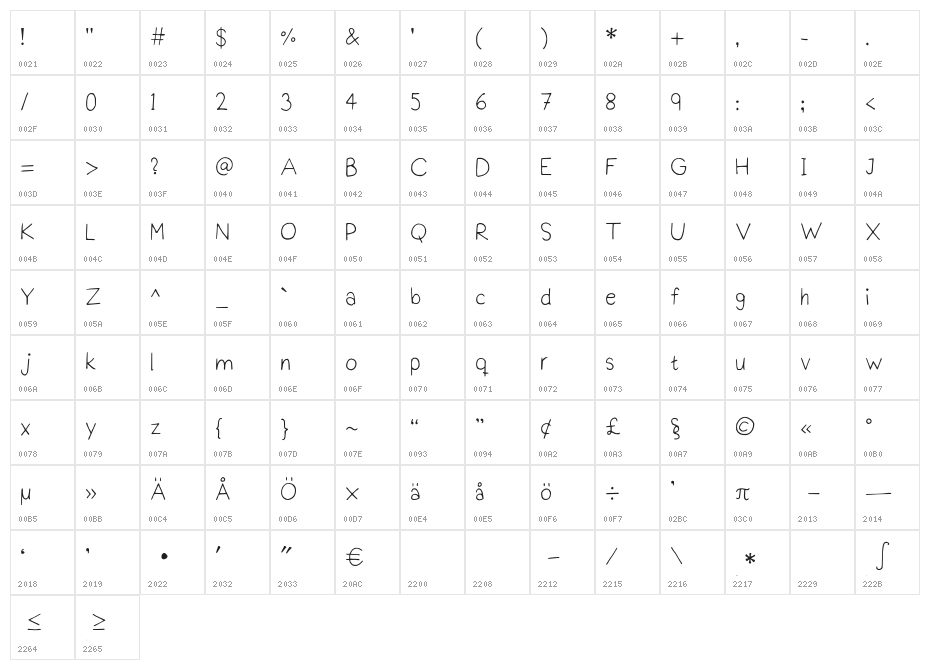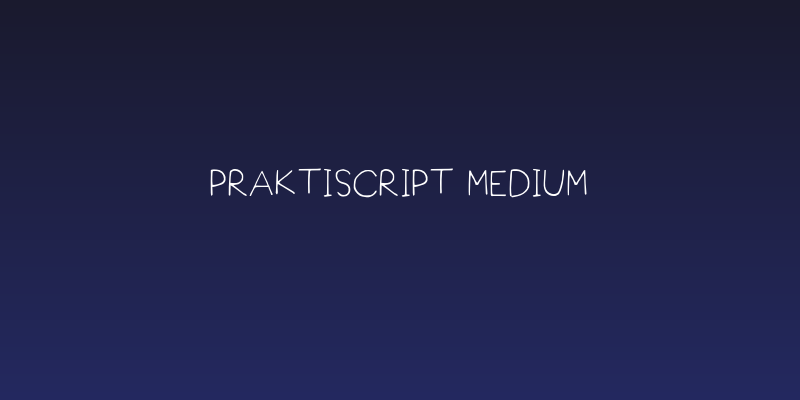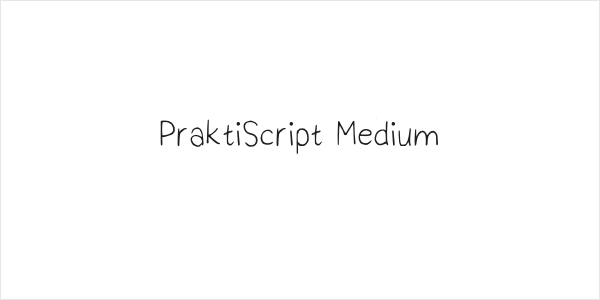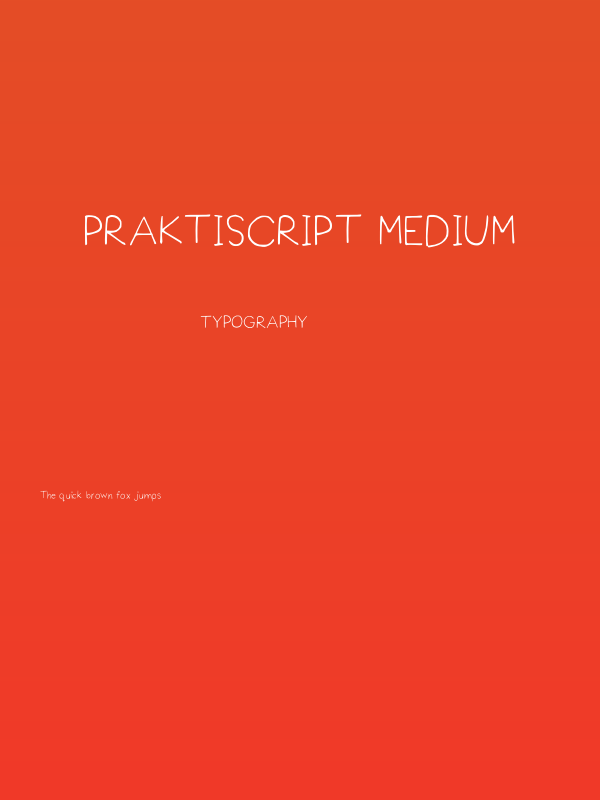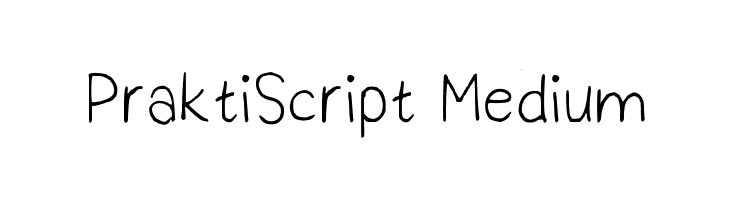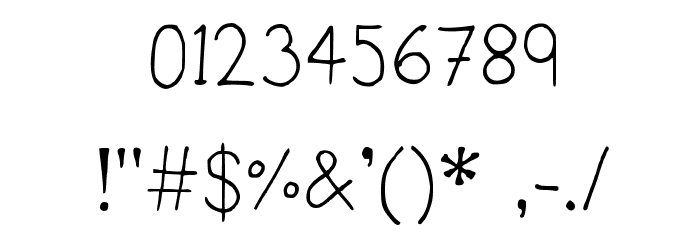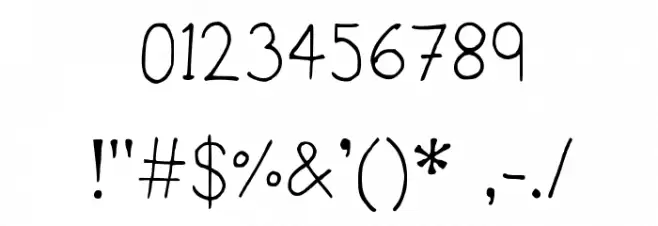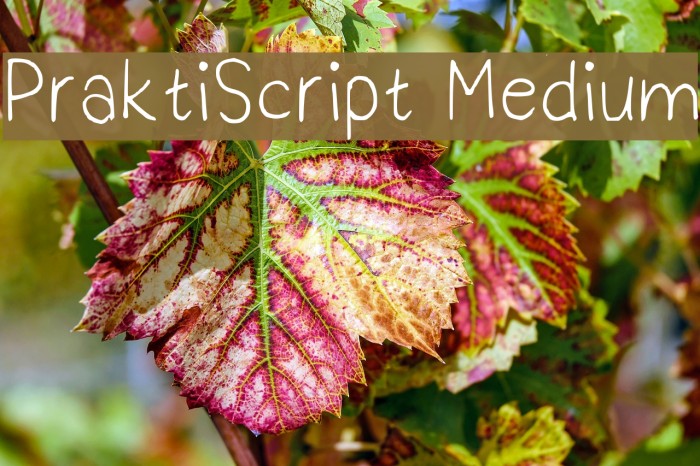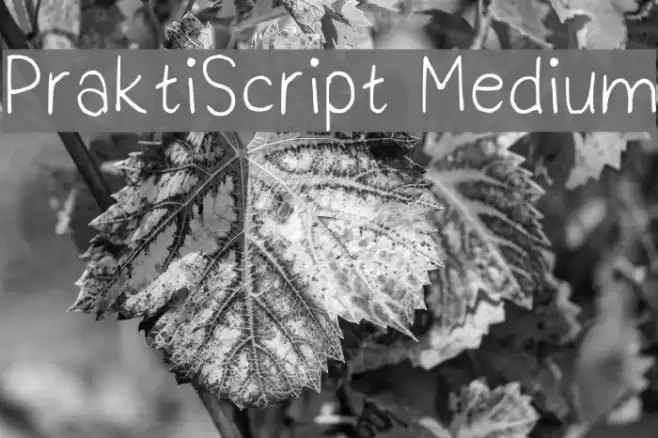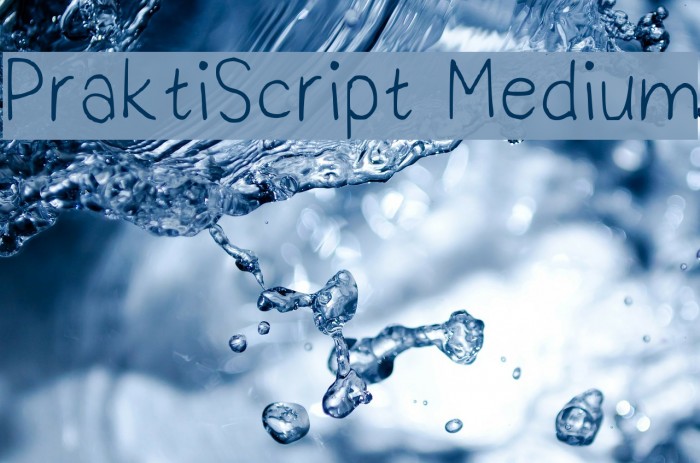
PraktiScript Medium Font
| Style général | Casual, Friendly |
| Cas d'utilisation | Headlines, Informal text, Creative projects |
| Projets proposés | Ideal for invitations, greeting cards, personal branding, and creative projects. |